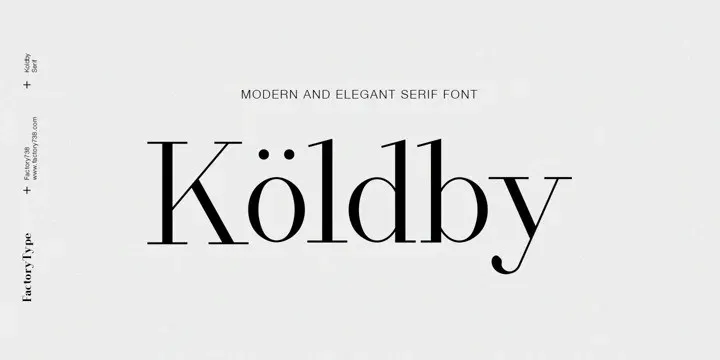
Koldby Font – Fonte Grátis
Koldby Font
A Koldby Font é uma elegante tipografia serifada que traz consigo uma personalidade atraente. Esta família de fontes combina elementos modernos com uma pegada vintage para criar um design arquitetônico e sofisticado, oferecendo um rico leque de opções de peso e estilo. Seus pesos variados permitem que você escolha o melhor tom tipográfico para seu projeto – os pesos mais leves são perfeitos para as fontes do corpo, enquanto os mais pesados se destacam como headlines altamente impactantes. Além disso, a disponibilidade de ligações estilísticas e alternativas oferecem uma variedade imensa de caracteres únicos que dão um toque inovador ao seu projeto ou logomarca. Ideal tanto para design editorial quanto para identidade visual, a Koldby Font é perfeita para quem busca estilo refinado e personalidade em suas criações visuais.